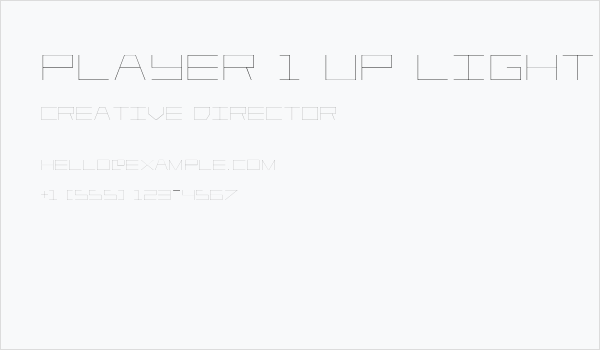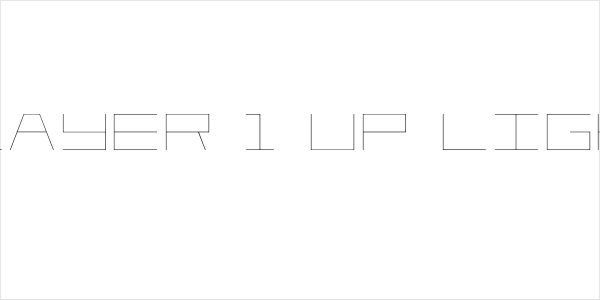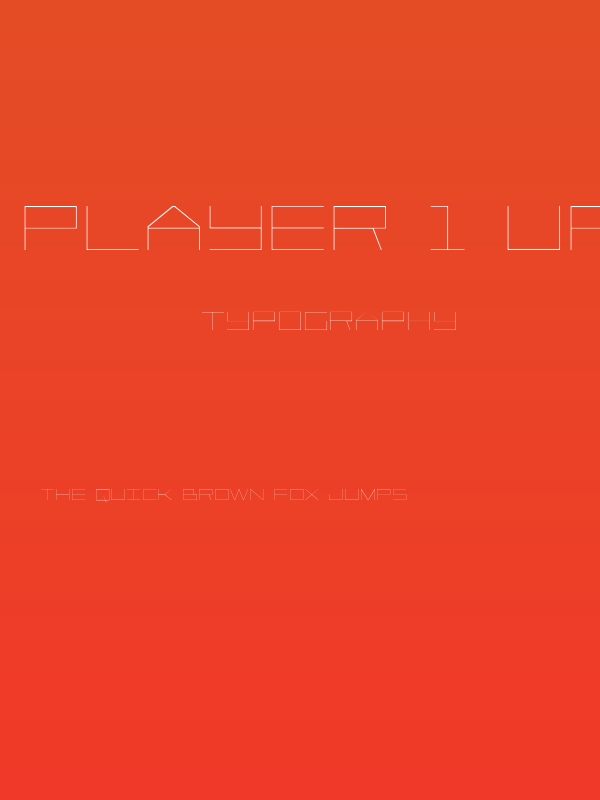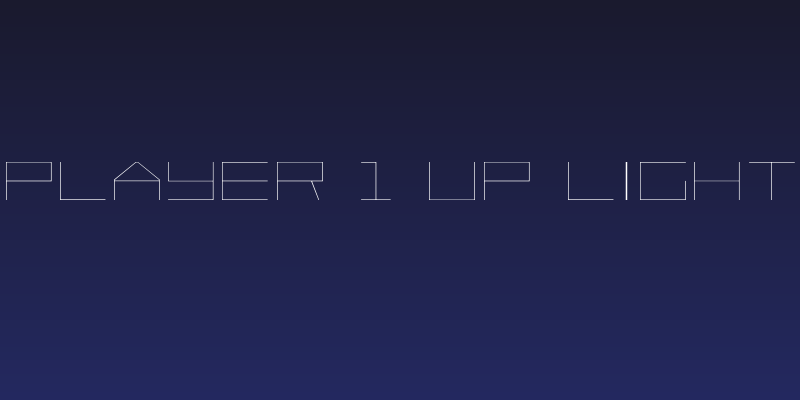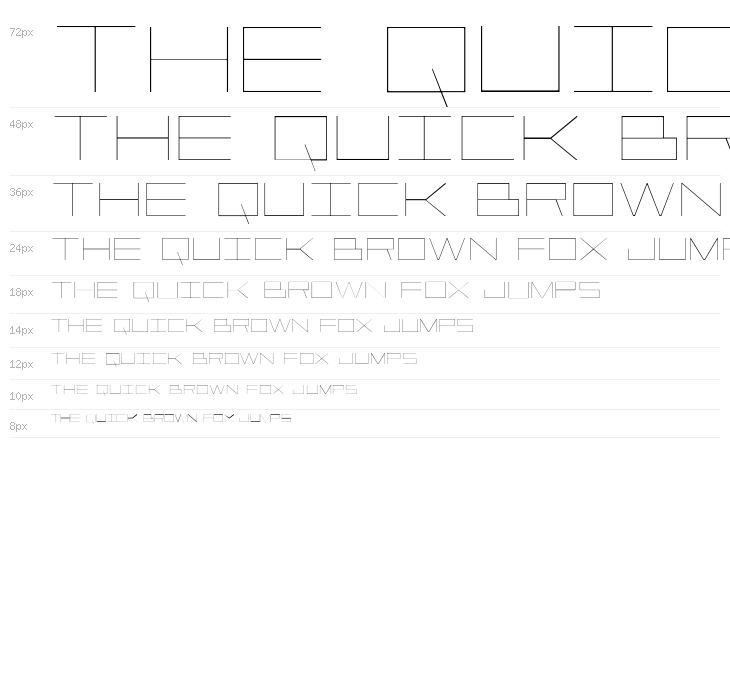
Player 1 Up Light Font
✎ Futuristic
| 分类 | Futuristic |
| 整体风格 | Futuristic, Minimalist |
| 使用场景 | Headlines, Digital interfaces, Branding |
| 推荐项目 | Ideal for tech branding, digital interfaces, video game titles, and modern posters. |